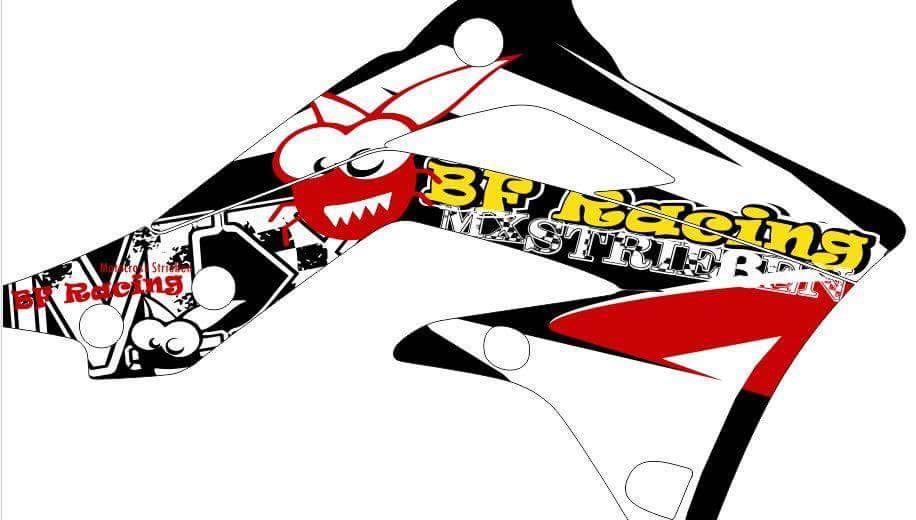
Schriftart mit Karo/Zielflagge gesucht
ich suche diese Schriftart.
Mit der das MX und MX-Strießen geschrieben wurde.
Ich weiß das ß stimmt nicht.
Werde ich dann anpassen.
Nee das ist sie nicht.
Es muss dieses Karomuster drin sein.
denn selbstgebastelt ist es nicht sieht man an dem ß denn das hat keine Flagge.